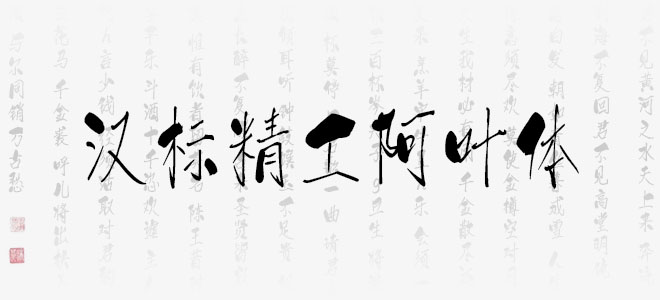
漢標精工阿葉體是一款硬筆和毛筆結(jié)合手寫書法字體,是由書法家阿良依托硬筆書法,結(jié)合規(guī)范書寫的要求而創(chuàng)作,整款字體規(guī)范、端正、清晰、簡潔,每個字都有枯枝發(fā)新芽的感覺,旨在通過這套字體的應(yīng)用,能增強書寫之美,讓屏顯和印刷的字具備書法美感。是剛?cè)嵯酀囊豢钭煮w。歡迎喜歡漢標精工阿葉體的朋友前來下載使用。
漢標精工阿葉體